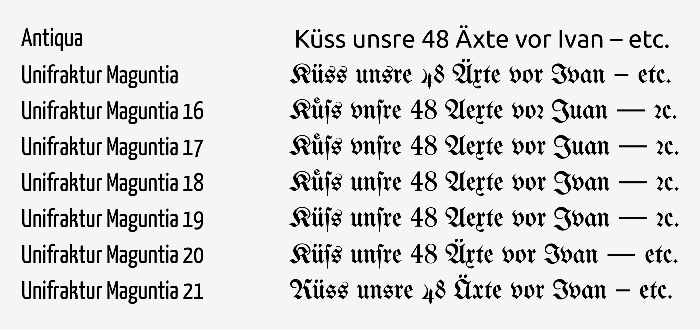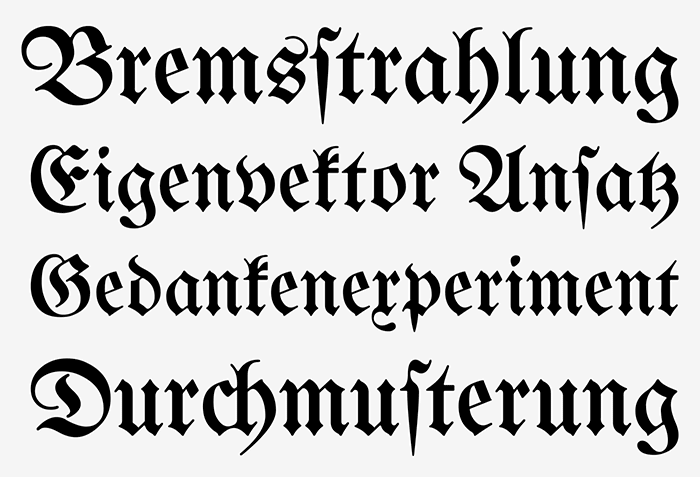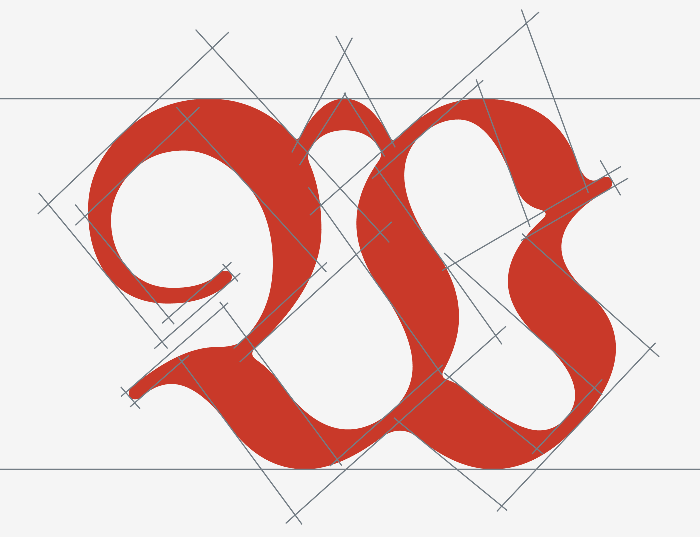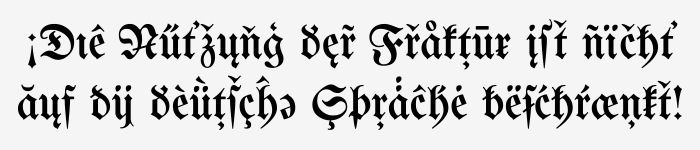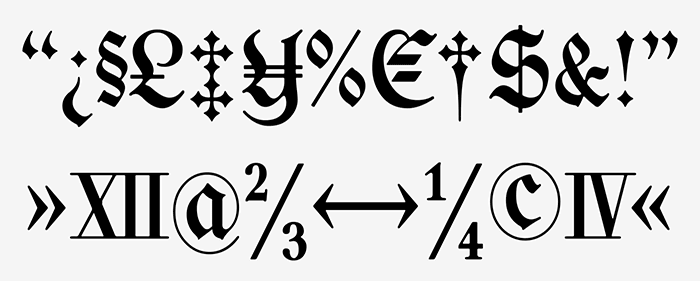
Interview zur gebrochenen Schrift Unifraktur Maguntia
Gerrit Ansmann hat in den letzten Jahren an der Unifraktur Maguntia gearbeitet – einer kostenlos verfügbaren gebrochenen Schrift mit umfangreichem Zeichenausbau und zahlreichen Smartfont-Merkmalen. In diesem Interview verrät er uns mehr über dieses Projekt.
Was fasziniert dich als Physiker an Typografie und Schriftgestaltung? Welche Motivation steckte hinter dem Ausbau der Unifraktur Maguntia?
Ich interessierte mich schon vor meinem Studium für Computergrafik, und dadurch, dass sie für wissenschaftliche Illustrationen nützlich wurde und Bézier-Kurven, Splines u. Ä. Gegenstand meiner Nebenfach-Vorlesungen in Numerik waren, verstärkte sich dies. Außerdem mag ich, im Vergleich zu anderen Künsten, die mathematische Natur der Schriftgestaltung. Aber mein Anlass, sich mit der Gestaltung von Frakturschriften zu beschäftigen, war ein ganz anderer: Als Physiker konnte ich mich naturgemäß für Rollenspiele begeistern, in meinem Fall Cthulhu. Dieses spielt hauptsächlich in den Zwanzigerjahren des vorherigen Jahrhunderts und ist sehr recherchelastig. Wer, wie ich, Abenteuer für dieses Spiel entwirft, muss daher häufig fiktive Zeitungsauschnitte u. Ä. erschaffen, die aus dieser Zeit stammen oder noch älter sind. Um den historischen Schriftsatz authentisch nachahmen zu können, arbeitete ich mich daher in die historischen Regeln des Fraktursatzes ein und lernte, das lange s und Ligaturen einzusetzen. In der Praxis hieß dies dummerweise häufig, dass ich irgendwelche Sonderzeichen per Hand einfügen musste, da die wenigsten Frakturschriften OpenType oder Unicode unterstützten. Die Maguntia war eine der wenigen Ausnahmen, basierte aber wie so viele Frakturschriften auf einer durchwachsenen Digitalisierung. Zum Beispiel hatte man in Wörtern wie Luftfahrt f- und t-Balken auf drei verschiedenen Höhen und J und I waren durch Skalieren ineinander überführbar. Da die Schrift frei war, fing ich daher irgendwann an, die schwerwiegendsten Probleme anzugehen, wobei mir neue Probleme auffielen, die ich wiederum behob, nur um irgendwann alles über den Haufen zu werfen und alle Buchstaben von Grundauf neu zu digitalisieren, und so weiter. Anfangs war mein Ansporn hierbei, eines Tages eine kleine Anleitung für historischen Fraktursatz zu schreiben, die dem Leser nicht abverlangt, irgendwelche sonstwo platzierten Sonderzeichen zu nutzen, sondern die Hauptarbeit OpenType u. Ä. zu überlassen.
Bald gesellte sich allerdings eine andere Motivation hinzu, und zwar, dass die meisten Schöpfer von Frakturschriften eher auf Masse statt auf Klasse zu setzen schienen und ich mir wünschte, dass es zumindest eine Frakturschrift gibt, mit der man alles tun konnte, was man sinnvoll mit Fraktur anstellen können wollte.
Auf welchen historischen Vorlagen basiert die Schrift? Und wie eng lehnt sich die Unifraktur Maguntia an diese an bzw. was wurde neu interpretiert oder neu hinzugefügt?
Die Hauptvorlage ist Carl Albert Fahrenwaldts Mainzer Fraktur von 1901, aus welcher die meisten Buchstaben und Ligaturen des deutschen Alphabets stammen, mit Ausnahme von J, Ä, Ö und Ü, die damals im Fraktursatz erst langsam in Gebrauch gerieten. Die verbleibenden Zeichen der Vorlage übernahm ich nur teilweise, da viele meines Erachtens nicht gut zum Rest der Schrift passten, vor allem die Ziffern und einige Satzzeichen. Diese Zeichen waren eher im Antiqua-Stil gehalten, was aber aus mir unerfindlichen Gründen damals üblich war – weswegen ich auch später Antiqua-Ziffern als Alternative ergänzte. Alle anderen Glyphen habe ich neugestaltet, wobei ich sofern sinnvoll möglich die existierenden Glyphen als Grundlage verwendet habe und mich von der ursprünglichen Maguntia und anderen Schriften hab inspirieren lassen. Dies betrifft unter anderem die modernen Formen, die Ziffern, Akzente und diverse Sonderzeichen.
Lesbarkeit vs. Tradition: Ist die Schrift eher für traditionellen Fraktursatz gedacht? Wie geht sie mit dessen heutigen Lesbarkeitsproblemen um?
Zum einen dienen viele Glyphen ausschließlich der Reproduktion historischer Texte, was ja auch eines der Paradigmata meiner Arbeit war: Jeder Frakturtext soll mit der Maguntia abgebildet werden können. Zum anderen habe ich von zehn Buchstaben, die ungeübten Lesern besonders Probleme bereiten, moderne Varianten gestaltet, sowie ein rundes s ohne Schwung, das am Anfang oder im Innern eines Wortes genutzt werden kann, also dort, wo historisch ein langes s stand. Bei der Gestaltung dieser modernen Varianten habe ich aber den Gestaltungsprinzipien der ursprünglichen Schrift Priorität eingeräumt und deshalb habe ich beispielsweise kein modernes T implementiert (da ich keine zufriedenstellende Lösung fand) und das moderne N ist noch weit von einem Antiqua-N entfernt. Die modernen Varianten sind also ein – hoffentlich guter – Kompromiss zwischen Lesbarkeit und einheitlichen Formen.
Beispielsatz, der die traditionellen und modernisierten Zeichenformen zeigt.
Traditionalisten möchten die Satzregeln und Zeichenformen in ihrem letztgültigen Stand beibehalten sehen, während andere argumentieren würden, dass modernisierte Formen und Satzregeln die gebrochenen Schrift eher am Leben halten können. Wie stehst du zu diesem Thema?
Ich denke nicht, dass man eine Schrift nutzen oder erschaffen sollte, nur um einen Stil am Leben zu erhalten. Stattdessen sollte man eine Schrift nutzen, wenn sie sich für eine Anwendung eignet, und eine Schrift erschaffen, wenn einem die Erschaffung selbst Freude bereitet oder man denkt, dass jemand diese Schrift nutzen möchte – in welchem Fall der Stil durch dieses Bedürfnis am Leben erhalten wird.
Ansonsten denke ich, dass sowohl historischer als auch moderner Fraktursatz ihre Existenzberechtigung haben, zum Beispiel: Wenn die Schrift nur »traditionell« oder (vor allem außerhalb des deutschen Sprachraums) »deutsch« kommunizieren soll und Lesbarkeit entscheidend ist, bietet es sich an, Modernisierungen zu nutzen. Soll die Schrift hingegen »historisch« oder »sehr alt« kommunizieren und es ist zu erwarten, dass die Leserschaft den Text mit angemessenem Aufwand entziffert bekommt, bietet es sich an, das lange s, historische Buchstabenformen usw. zu nutzen. Nichtsdestotrotz habe ich kein Verständnis für unsinnig absurde Kombinationen oder gescheiterte Versuche historisch zu sein, die mit einer Minute Internet-Recherche vermieden werden können. Der wohl verbreiteste derartige Fehler ist die pauschale Ersetzung des runden s durch das lange. Ein anderes Beispiel ist das neue Warsteiner-Logo, dessen t am ehesten wie ein Fraktur-k aussieht, wenn überhaupt, aber weder wie ein Fraktur-t noch wie ein Antiqua-t.
Gebrochene Schriften sind heute im deutschsprachigen Raum nur noch selten im Einsatz und wenn doch, nicht selten mit ausdrücklich gewünschter oder ungewollt entstehender Assoziationen zum Nationalsozialismus. Lässt sich die gebrochene Schrift überhaupt noch davon lösen und welche Einsätze stellst du dir für deine Schrift vor?
Meiner Erfahrung nach hat die Fraktur in Deutschland durchaus ihre Nischen, in denen sie nicht automatisch mit den Nazis assoziiert wird, zum Beispiel in den Kontexten Tradition, Geschichte oder Festlichkeiten. Außerhalb des deutschen Sprachraums kann die Situation ähnlich sein, gerade wo irgendwann einmal Fraktur üblich war, z. B. habe ich eine beachtliche Menge Fraktur in Prag gesehen. Zumindest in Teilen des Rests der Welt wird Fraktur erst einmal mit Deutschland assoziiert (was leider häufig selbst für eine Nazi-Assoziation reicht), aber auch hier kommt es auf Kontext und Ort an. Außerhalb dieser Nischen besteht gibt es m. E. weder Chancen noch die Notwendigkeit, eine gewisse Nazi-Assoziation zu überwinden. Wer will schon z. B. seine politischen Standpunkte als »historisch« oder »alt« vermarkten?
Ein anderes Problem stellen leider kleine Auflösungen dar, bei denen es sich bemerkbar macht, dass die Hinting-Technik einfach nicht für Fraktur gemacht ist. Ich habe zwar hoffentlich einiges verbessert, indem ich Linienbreiten und -positionen angeglichen habe und viele Stämme per Hand markiert habe, aber für manuelles Hinting auf der Bitmap-Ebene fehlt mir dann doch die Muße.